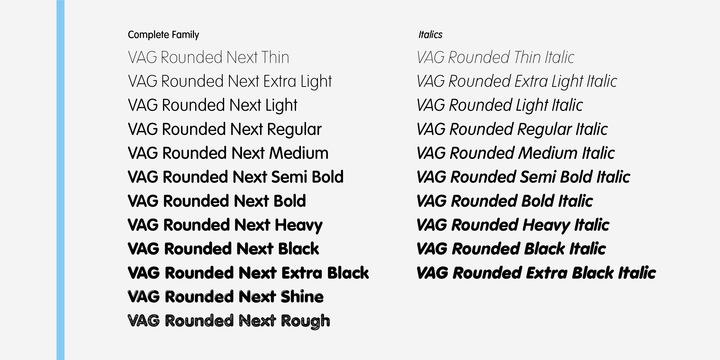
Обзор линотипаРазработанный для Volkswagen AG в 1979 году, VAG Rounded представляет собой модификацию гротесков 19 века. Исключением в этом шрифте являются закругленные окончания штрихов. Используйте этот шрифт для технических текстов, руководств по эксплуатации или рекламы. Закругленная история VAG
Дизайн VAG Rounded изначально был задуман как фирменный шрифт для Volkswagen AG, мирового автомобильного гиганта. У него немного туманная история с несколькими дизайнерами, участвующими во всем процессе; он был завершен дизайнерской компанией Sedley Place в Лондоне по заказу швейцарских маркетинговых агентов VW в то время. Sedley Place была брендинговой и маркетинговой компанией, созданной членами маркетинговой группы VW, и до сих пор существует как мощная сила в мире элитного маркетинга.
Предысторией создания дизайна VAG Rounded был другой известный автопроизводитель Audi, которого VW приобрел в 1964 году. В начале 1970-х годов, когда дилерские сети Audi/VW уже начали объединяться, стратегию корпоративного брендинга пришлось изменить. чтобы удовлетворить маркетинговые потребности этих основных частей группы, чьи дилеры теперь использовали одни и те же торговые точки. В комиссию за новый шрифт как часть их фирменного стиля входили не только Volkswagen и Audi, но и их компании VAG Bank и VAG Leasing.
Не было простого способа объединить существующие идентичности шрифтов Audi / VW с Audi, использующими шрифт Times с полной засечкой, и VW, использующий шрифт Futura, разработанный в 1927 году. Художественный и креативный директор решили, что требуется совершенно новый шрифт, поэтому родилась концепция шрифта с закругленными концами в качестве основы для их типографского брендинга. Первоначально созданный вручную, дизайн VAG Rounded позже был усовершенствован с помощью компьютера PDP-8.
Шрифт VAG Rounded впоследствии использовался во всех корпоративных и дилерских публикациях VW, Audi VAG Bank и VAG leasing до конца восьмидесятых, когда VW начал очередной раунд ребрендинга. Дизайн VAG Rounded использовался VW до 19 года.92.
Шрифт должен был быть доступен по всему миру, чтобы дилеры могли продолжить брендинг, включающий дизайн VAG Rounded, поскольку он использовался в их литературе, вывесках и рекламе. Чтобы улучшить доступность, VW выпустил дизайн VAG Rounded в общественное достояние, что также позволило объединить его с большей частью доступного программного обеспечения для настольных издательских систем, доступного в то время. Это открыло возможность миллионам пользователей компьютеров использовать бесплатную лицензию VAG Rounded, одновременно укрепляя бренд VW.
В последнее время VAG Rounded стал привычным зрелищем. На ряде издательских сайтов Web 2.0 он использовался в онлайн-логотипах, где закругленные концы делают текст более неформальным, придавая дружественный вид.
VAG Rounded — это то, что часто называют «фирменным» шрифтом. Этот закругленный шрифт без засечек широко использовался (особенно в Интернете) для создания очень гладких и дружелюбных логотипов. Skype и MySpace — два самых известных примера компаний, использующих дизайн VAG Rounded в своих онлайн-логотипах.
Apple использовала дизайн VAG Rounded на клавишах клавиатуры своих iBooks и PowerBooks, что еще больше повысило привлекательность этого семейства шрифтов. General Electric сочла целесообразным использовать его в качестве основы для своего фирменного шрифта GE Inspira, используемого для маркировки их продуктов.